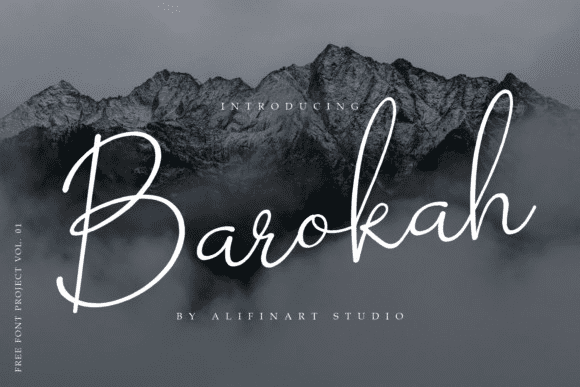
Название: Barokah Font
Барока - это уникальный и элегантный шрифт.
Этот шрифт сочетает в себе мягкий и смелый дизайн, который является отличительной чертой фирменного шрифта.
Основным вдохновением для этого шрифта является рукописный стиль письма с использованием чернильного пера.